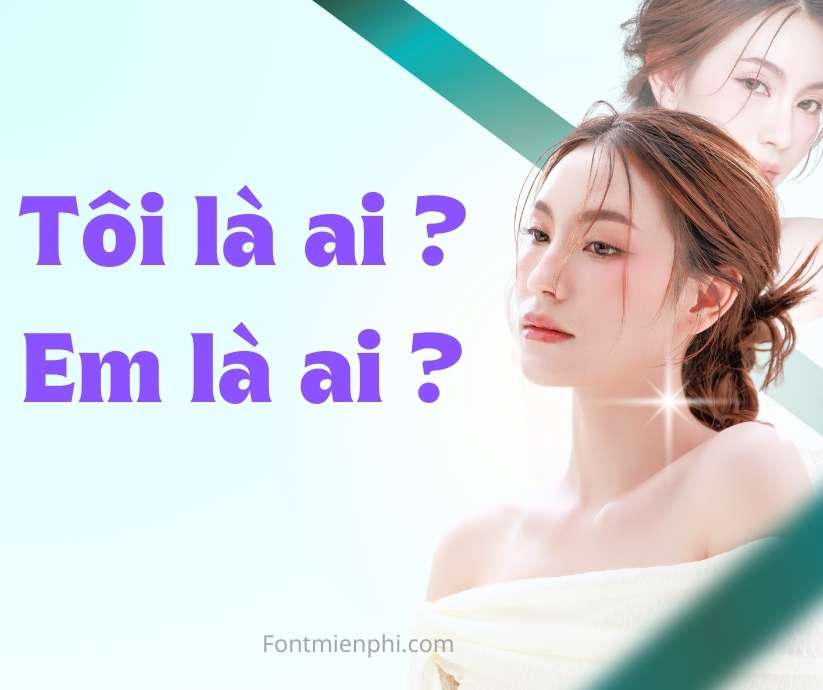
Font Việt hóa VIP Brick Records
Font Việt hóa VIP Brick Records: Thổi Hồn Âm Nhạc Và Chất Retro Vào Thiết Kế Của Bạn
Nhắc đến các thiết kế mang phong cách cổ điển, đường phố hay âm nhạc nghệ thuật, Typography luôn đóng một vai trò cực kỳ quan trọng. Để tạo ra một ấn phẩm ấn tượng, thu hút ánh nhìn ngay từ giây đầu tiên, bạn không thể bỏ qua Font Việt hóa VIP Brick Records. Đây là một trong những bộ phông chữ đang được cộng đồng Designer săn đón nhờ vào phong cách thiết kế độc bản và tính ứng dụng cực cao.
Brick Records là gì? Đúng như tên gọi của mình, “Brick Records” lấy cảm hứng từ những hãng thu âm (records) của những thập niên trước, kết hợp với âm hưởng của văn hóa đường phố (streetwear) và đĩa than (vinyl). Các nét chữ được thiết kế dày dặn, vững chãi (brick – viên gạch) nhưng lại có độ lơi và những đường bo góc đầy tính nghệ thuật. Tổng thể phông chữ mang lại một cảm giác vừa hoài niệm, vintage nhưng cũng rất cá tính và mạnh mẽ.
Tại sao bạn nên sở hữu Font Việt hóa VIP Brick Records? Phiên bản gốc của Brick Records vốn đã rất xuất sắc, nhưng rào cản lớn nhất đối với các nhà thiết kế Việt Nam chính là lỗi font khi gõ dấu. Với phiên bản VIP Brick Records Việt hóa, mọi vấn đề đã được giải quyết triệt để:
Hỗ trợ tiếng Việt hoàn hảo: Font chữ đã được thêm dấu tiếng Việt thủ công, chăm chút từng dấu ngã, dấu hỏi để đảm bảo tính thẩm mỹ đồng bộ với nét chữ gốc.
Kerning chuẩn xác: Khoảng cách giữa các ký tự (kerning) được tinh chỉnh lại tỉ mỉ, giúp những đoạn văn bản ngắn hay các tiêu đề lớn (Headline) trông cân đối và chuyên nghiệp mà không cần bạn phải tracking bằng tay.
Ứng dụng thực tế trong thiết kế Sự linh hoạt của Font Brick Records Việt hóa giúp nó tỏa sáng trong nhiều dự án khác nhau:
Ngành công nghiệp giải trí: Tuyệt vời để làm typography cho bìa album nhạc, poster show diễn, nghệ sĩ Indie/Underground.
Nhận diện thương hiệu: Phù hợp làm logo cho các quán cafe acoustic, thương hiệu thời trang local brand mang hơi hướng retro, bụi bặm.
Ấn phẩm truyền thông: Sử dụng làm tiêu đề cho banner quảng cáo, bài đăng mạng xã hội (Social Media) cần sự nổi bật và mang đậm cá tính riêng.